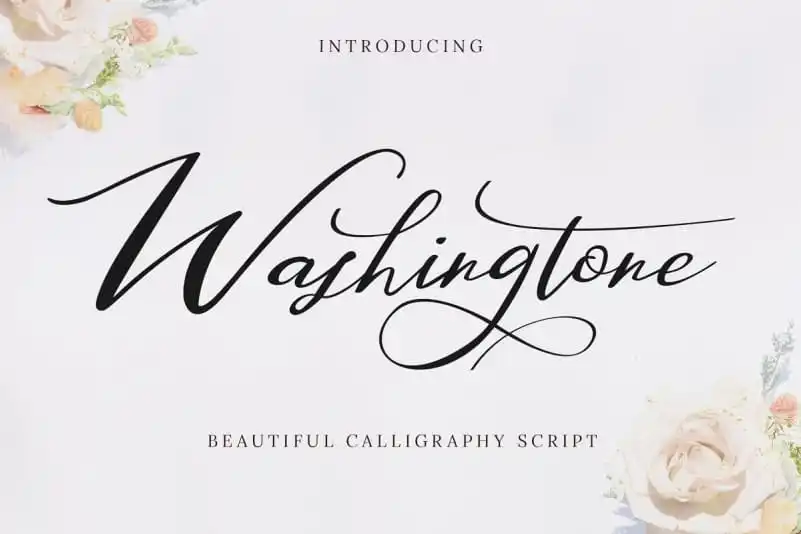
Washingtone Calligraphy Font – Download Grátis
A Washingtone Calligraphy Font é inspirada no tipo clássico e traz seu próprio estilo único para projetos de design. Este tipo foi criado e compartilhado pela Masdika Studio, que oferece um script elegante e sofisticado com muitas alternativas estilísticas. Com uma escrita natural da mão, é perfeito para uso em headlines, logotipos, roupas, convites, marcações, embalagens e anúncios. Essa fonte de script é a escolha perfeita para quem procura um estilo único para suas propostas visuais. A Washingtone Calligraphy Font está à disposição como uma excelente opção para aqueles que buscam adicionar personalidade e elegância aos seus projetos gráficos.